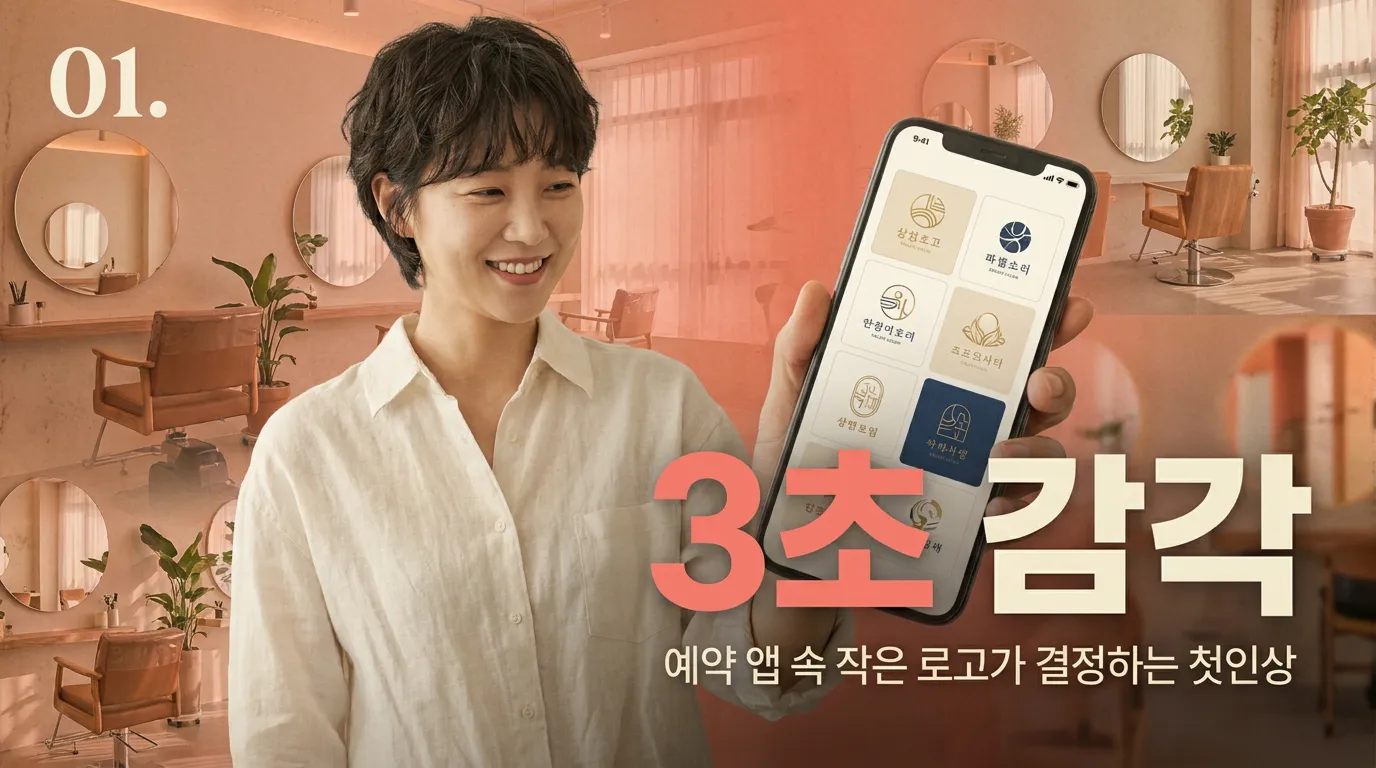
헤어샵 로고 디자인, 손님이 3초 만에 감각 있다고 느끼는 폰트·색 조합 7개
헤어샵 로고에서 촌스러워 보이는 조합을 피하고, 샵 콘셉트별로 바로 적용할 수 있는 폰트와 컬러 기준을 정리했습니다.
예약 앱에서 샵 이름이 작게 떴는데, 손님은 이미 ‘여기 감각 괜찮겠다’까지 판단합니다.
왜 예쁜 필기체가 오히려 싸 보일까요?
헤어샵 로고에서 가장 많이 망가지는 지점이 ‘여성스럽게’ 보이려고 얇은 필기체를 고르는 순간입니다. 문제는 곡선이 아니라 간격입니다. 글자끼리 붙고, 획 굵기가 너무 가늘면 인스타 프로필·네이버 예약 썸네일에서 그냥 실처럼 뭉개집니다.
저라면 영문은 하이 콘트라스트 세리프보다, 획 끝이 정리된 모던 세리프나 부드러운 산세리프를 먼저 봅니다. 한글 상호라면 둥근 고딕을 그대로 쓰지 말고 자간을 5~20 정도 넓혀보세요. ‘친절한 샵’이 아니라 ‘관리된 샵’처럼 보입니다.
KISS에 등재된 타이포그래피 감성 전달 연구도 서체 유형이 감성 이미지 인식에 영향을 준다고 봤습니다. 디자인 전공자 240명을 대상으로 한 실험이었는데, 저는 이 대목이 현장과 맞다고 봅니다. 폰트는 장식이 아니라 첫 말투입니다. (kiss.kstudy.com)
블랙 로고는 다 고급스러울까요?
아닙니다. 블랙 하나만 쓰면 고급이 아니라 ‘무표정’이 될 때가 많습니다. 특히 화이트 벽, 베이지 우드, 거울 많은 헤어샵에서는 순검정 로고가 공간과 따로 놀 수 있습니다.
원장님 샵이 프리미엄 컷·클리닉 중심이면 차콜 #232323에 샴페인 베이지 #D8C6A3를 붙이세요. 염색과 트렌드 시술이 강하면 잉크 네이비 #1D2A3A에 뮤트 라벤더 #B8A7C9가 낫습니다. 내추럴·두피케어 쪽이면 올리브 그레이 #7C8068에 아이보리 #F4EFE6이 안전합니다.
색은 많이 쓰는 게 아니라 ‘하나를 덜어내는’ 쪽이 세련돼 보입니다. 로고 본색 1개, 보조색 1개, 배경색 1개. 이 3개를 넘기면 헤어샵보다 화장품 샘플 팔레트처럼 보입니다.
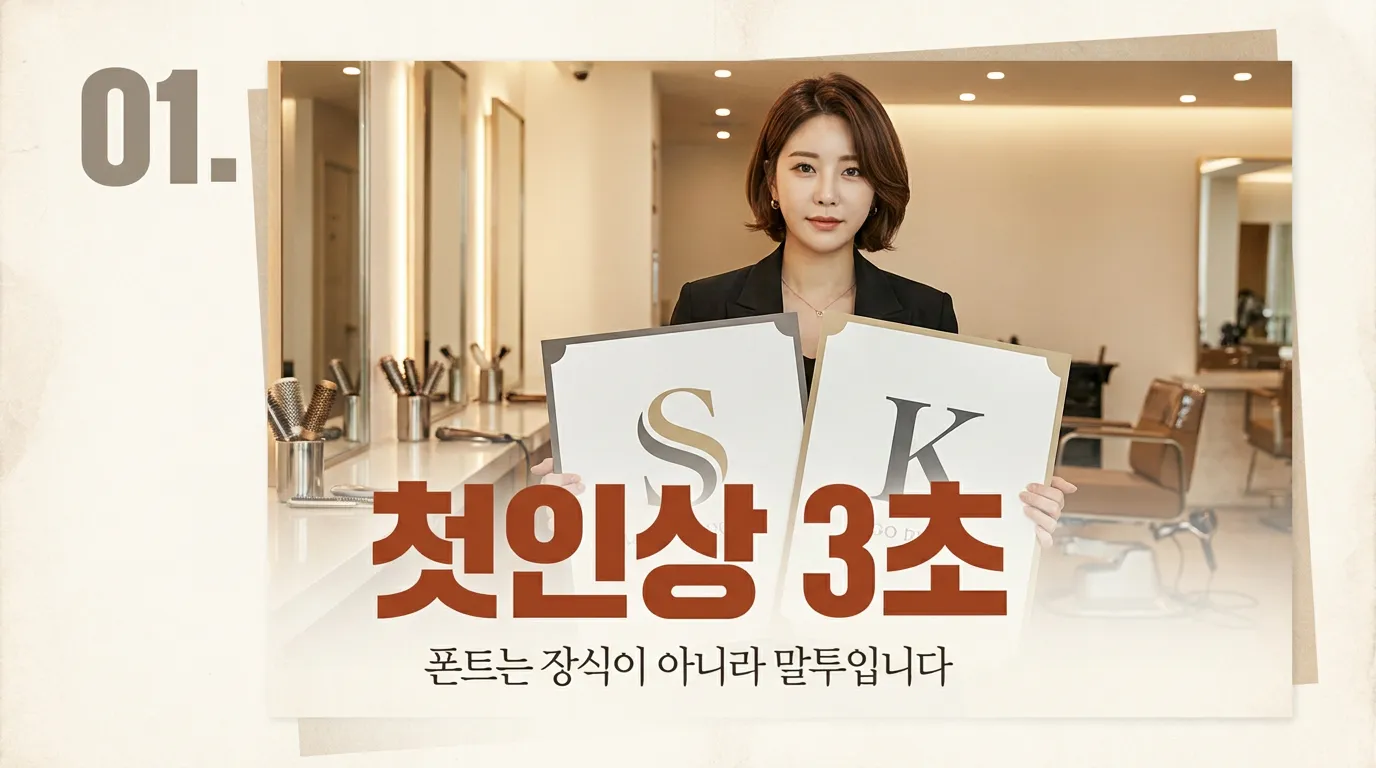
상호가 길면 어떤 폰트가 버틸까요?
상호가 6글자 이상이면 얇은 명조나 손글씨는 피하는 편이 좋습니다. 멀리서 읽히기 전, 먼저 ‘복잡하다’는 인상이 옵니다. 긴 이름은 개성을 폰트에 몰아넣지 말고, 글자 폭과 줄임 심볼로 풀어야 합니다.
예를 들어 ‘살롱드○○○’처럼 긴 이름은 전체를 로고로 밀지 말고, SALON은 작게, 핵심 이름은 크게, 심볼은 이니셜 하나로 정리하세요. 마크에서 헤어·뷰티 로고를 잡을 때도 처음부터 간판보다 예약 화면, 가격표, 시술 가운 자수까지 줄여 봅니다. 작아졌을 때 남는 것만 진짜 로고입니다.
통계청의 2024년 전국사업체조사 잠정 결과를 보면 국내 사업체는 635만 3,673개로 전년보다 늘었습니다. 동네 상권에서 ‘그냥 예쁜 로고’는 금방 묻힌다는 뜻이에요. 작은 화면에서 먼저 읽히는 로고가 손님 기억에 남습니다. (d-planet-00.tistory.com)
바로 써도 되는 조합은 뭔가요?
첫째, 미니멀 프리미엄형. 모던 세리프 + 차콜 + 샴페인 베이지. 컷 가격대가 높거나 1인 예약제 샵에 맞습니다.
둘째, 트렌디 컬러형. 라운드 산세리프 + 잉크 네이비 + 뮤트 라벤더. 염색, 레이어드컷, 2030 고객 비중이 높을 때 좋습니다.
셋째, 내추럴 케어형. 담백한 고딕 + 올리브 그레이 + 웜 아이보리. 두피관리, 클리닉, 편안한 상담을 앞세우는 샵에 어울립니다.
지금 당장 할 행동 한 줄: 샵 이름을 검정·차콜·베이지 3가지로만 적어보고, 스마트폰 화면에서 3초 안에 읽히는 조합만 남기세요.